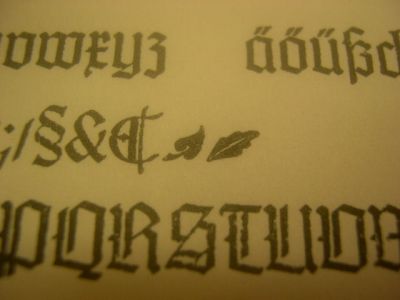
Wortbild – Akasha
ich wollte mal so ins Forum fragen, was der versierte Typograf zu diesem
Logo mit der modifizierten Monotype Corsiva sagt. Vor allem in Bezug auf
Buchstabenabstände, Buchstabenform und eventuell kritische Stellen.
Historisch gesehen, gab es in Zeichensätzen von Schriften in der Vergangenheit immer einmal wieder ein Blatt. Sie wurden als Alternative für Geburt und Tod eingesetzt, die ansonsten üblicherweise mit * und Todeskreuz dargestellt wurden:
Man assoziiert es mit Leben.
Das Logo zeigt einen Schriftzug AKasha - ich meine: es sind Versal A und K, richtig? Falls nicht, wäre doch die Oberlänge des Gemeinen k zu lang. Bzw. gäbe es keinen Grund, die Oberlängen des k und des h unterschiedlich zu gestalten.
Ich persönlich finde den Abstand zwischen sh zu groß. Aber eher marginal. Und wenn das AK wirklich zwei Versalien sind, hast Du mal versucht, sie wie bei einer Ligatur noch enger aneinander zu rücken?
Wohlgemerkt: Ich bin kein Typograph, nur Schriftsetzer. Und dazu noch ein alter müder Mann, der ansonsten nur noch seinen Bleisatz streichelt. Aber das Blatt ist wirklich hübsch.
Finde das Logo sehr schön, auch die Idee dahinter ist sehr geil!
Die Einkerbungen in dem Blatt sind allerdings sehr klein, die werden wohl abhanden gehen, wenn das ganze noch weiter runter skaliert wird.
Ich finde allerdings, dass das Logo ein bißchen linkslastig ist!? Vielleicht kann man dem entgegenwirken, wenn man eine sh Ligatur setzt, oder einen Endswash am a. oder aber, den oberen Swash des A ein bißchen weitläufiger macht!?! (Wie nennt man den Swash eigentlich am besten auf deutsch?)
Wie nennt man den Swash eigentlich am besten auf deutsch?
Ein Swash ist der ganze Zierbuchstabe, ein Flourish der Schnörkel. Du willst also den Schnörkel beim Zierbuchstaben A verändern :wink:
Mir gefällt das Logo auch gut. Ich sehe nur einen Schatten links neben dem Blatt, der für mich da nicht hingehört ...
Wenn das Logo kleiner gedruckt wird, werden wahrscheinlich die Lücken zwischen as und ha verschwinden. Warum nicht also gleich diese Buchstaben gewollt verbinden wie bei Ak? Die sh-Ligatur würde ich vielleicht mal probieren, sie könnte aber auch zuviel des Guten sein und den Blatt-Eye-Catcher abschwächen. Die Linkslastigkeit durch das k mit Blatt finde ich nicht störend. Das Blatt passt gut zum floralen Duktus der Schrift.
Wofür ist dieses Logo?
Grundsätzlich sehr schön.
Zwei Anregungen zum Ausprobieren:
- braucht es den Schatten?
- würde eine Mittel-Blattader das Blatt aufhellen (und könnte sie zusätzlich die Krümmung darstellen, für die derzeit der Schatten benötigt wird)? Könnte natürlich auch ein Zuviel sein, das muss ausprobiert werden um es sagen zu können.
Ich möchte ja die gute Stimmung nicht trüben – aber mir gefällt das Logo (noch) nicht so richtig. Man müsste vielleicht den Kontext kennen: Ich assoziiere Bio-Kosmetik, auch – vielleicht wegen dem Namen – etwas Esoterisches; die Idee mit dem Blatt ist natürlich schön. Für mich hat das Ganze jedoch noch zu sehr etwas gezwungenes: die Verbindung zwischen A und k, das Blättchen, das mitten in die geschwungenen Linien hineinsprießt: Man versteht die Idee… aber für mich swingt es noch nicht richtig, sieht es noch zu sehr nach Goldschmiedekunst am Bildschirm aus.
So wie ich das jetzt ausprobiert habe, empfinde ich den Schatten als
glücklichere Wahl. Durch die Mittelblattader geht das Scherenschnitt-artige verloren, das ich eigentlich recht gerne mochte. (Und eigentlich
mag ich auch den Schatten irgendwie.)
Beim Verbinden von "as" und "ha" bin ich mir auch unschlüssig. Ich
empfand es vorher irgendwie stimmiger.
Aber die Oberlänge vom "k" war wohl wirklich etwas zu lang und die
Einkerbungen am Blatt könnten wirklich etwas größer sein.
Meint ihr mit Ligatur zwischen "sh" so einen Schnörkel wie es sie bei der
Ms Eaves gibt?
Ach so, zur Erklärung. Das soll der Schriftzug für einen Kurzfilm sein.
Wenn die Assotioationen in Richtung Geburt und Tod, sowie ein bisschen
in Richtung Esoterik gehen, dann passt es soweit eigentlich ganz gut.
mir so, als ob der Duktus links oben etwas zu dick ist im Vergleich zu den
anderen Strichstärken. Kann aber auch sein, dass ich mich täusche.
kommt mir auch so vor, chsc.
sieht etwas komisch aus.
mit der ligatur gebe ich dir recht, rené
sieht gut aus, lengt aber ab.
die spitzen sind auch besser, auch wenn ich sie noch mehr
abgestumpft hätte. wenn es dir gefällt, dann las
das logo so, gelungen ist es allemal
und der rest im vielleicht auch geschmackssache ...